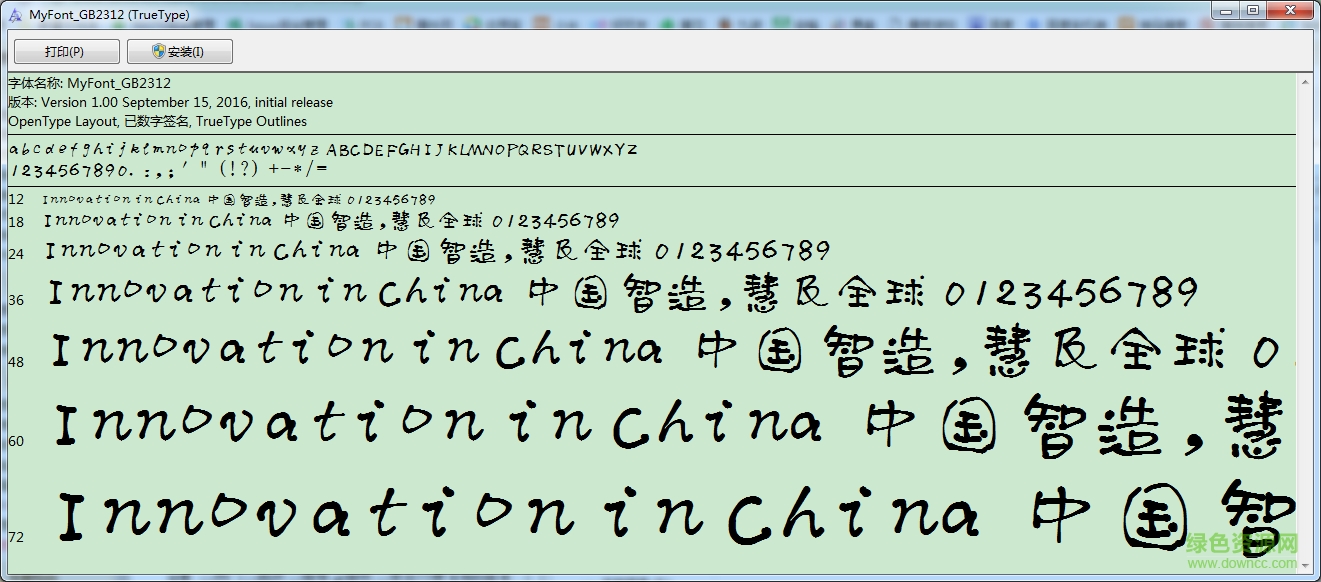
默陌肥圓水墨體字體
默陌肥圓水墨體是銳字家族推出的一款古風(fēng)水墨字體,也稱作默陌肥圓手寫體,字跡如同墨跡填充,十分古色生香,給人毛筆書法字體的美好呈現(xiàn),如果你喜歡,就來綠色資源網(wǎng)收藏吧!
默陌肥圓水墨體字體介紹
默陌肥圓手寫體字形豐腴圓潤,采用輕松自由的水墨筆觸,筆畫節(jié)點隨性、不拘小節(jié)。風(fēng)格適用于pop廣告類海報和各種圖文配字。
默陌肥圓水墨手寫體點評
默陌肥圓水墨字體,兼具毛筆字體卡通字體的美好特色,給人十分舒適的視覺體驗,文字圓潤而清揚,可以使用在平面設(shè)計、海報設(shè)計等場合。